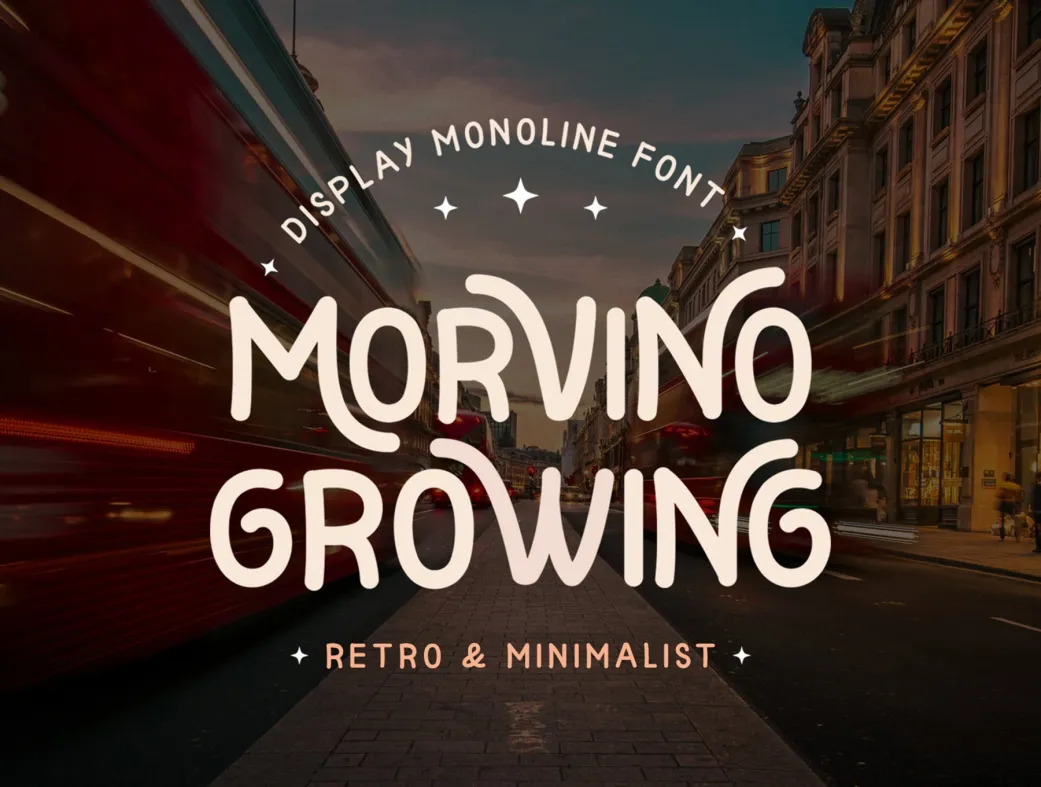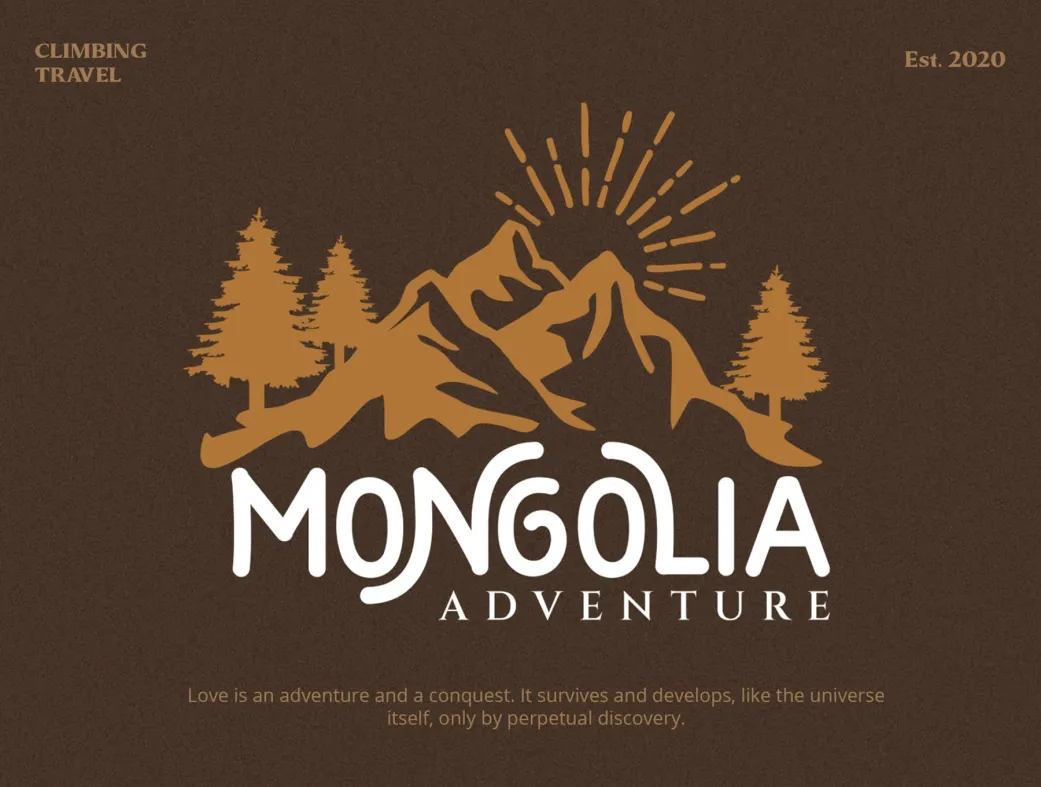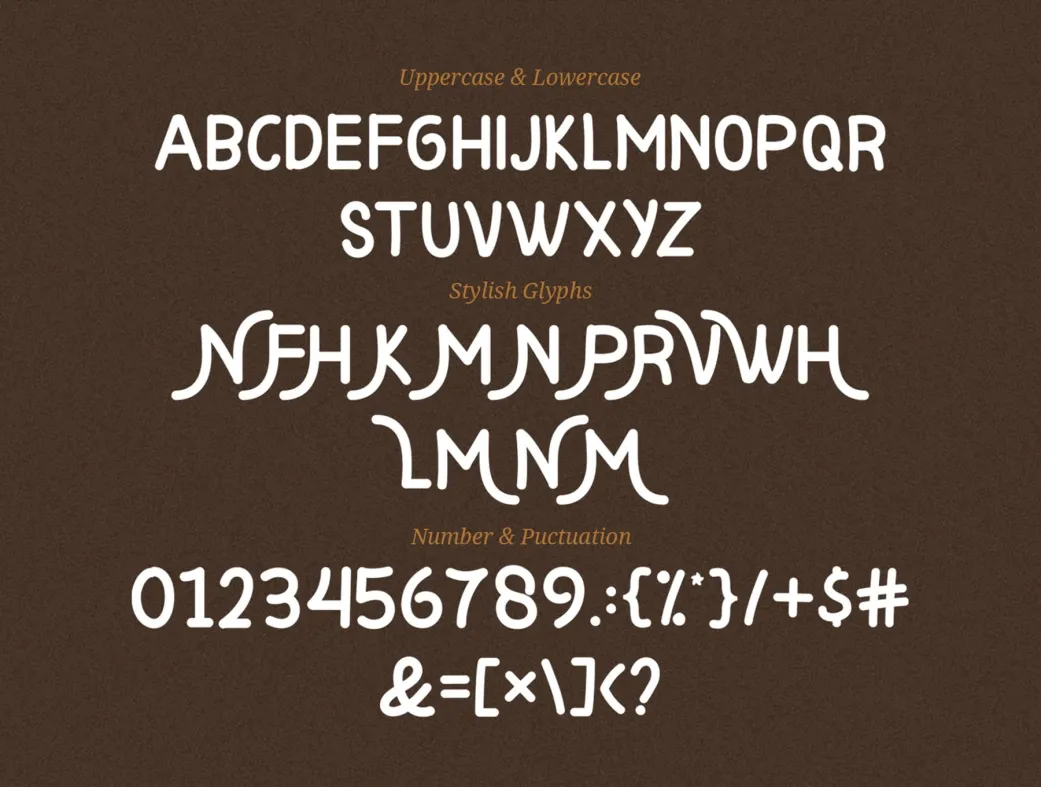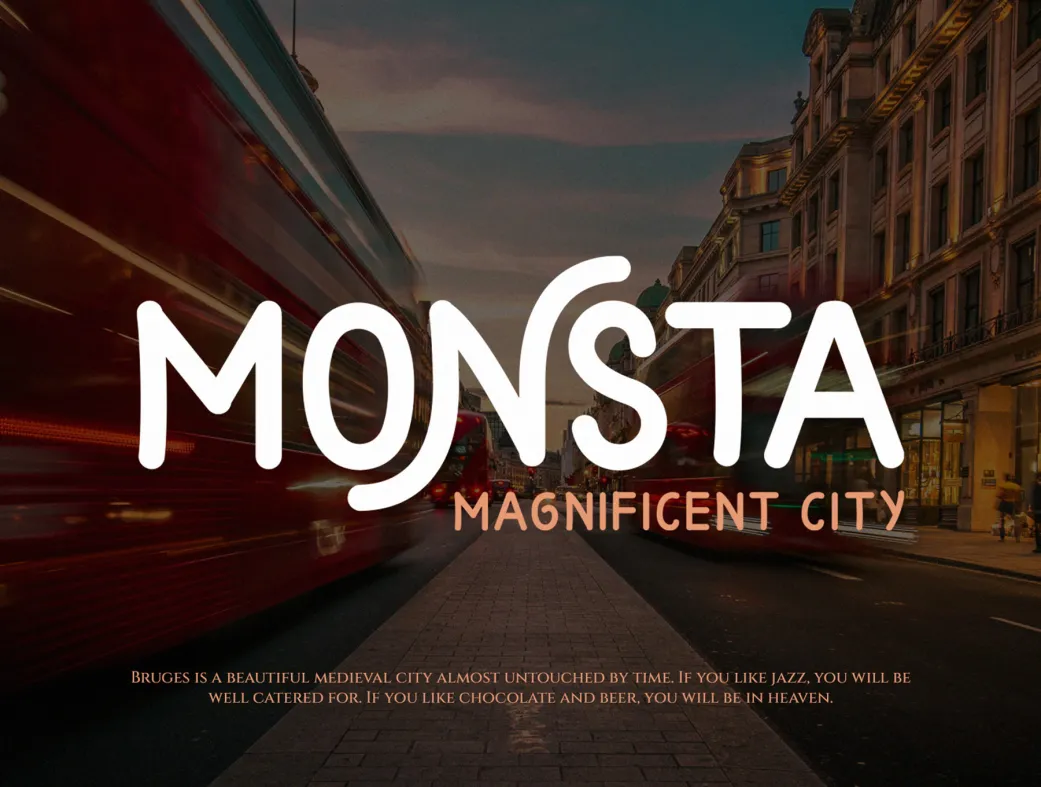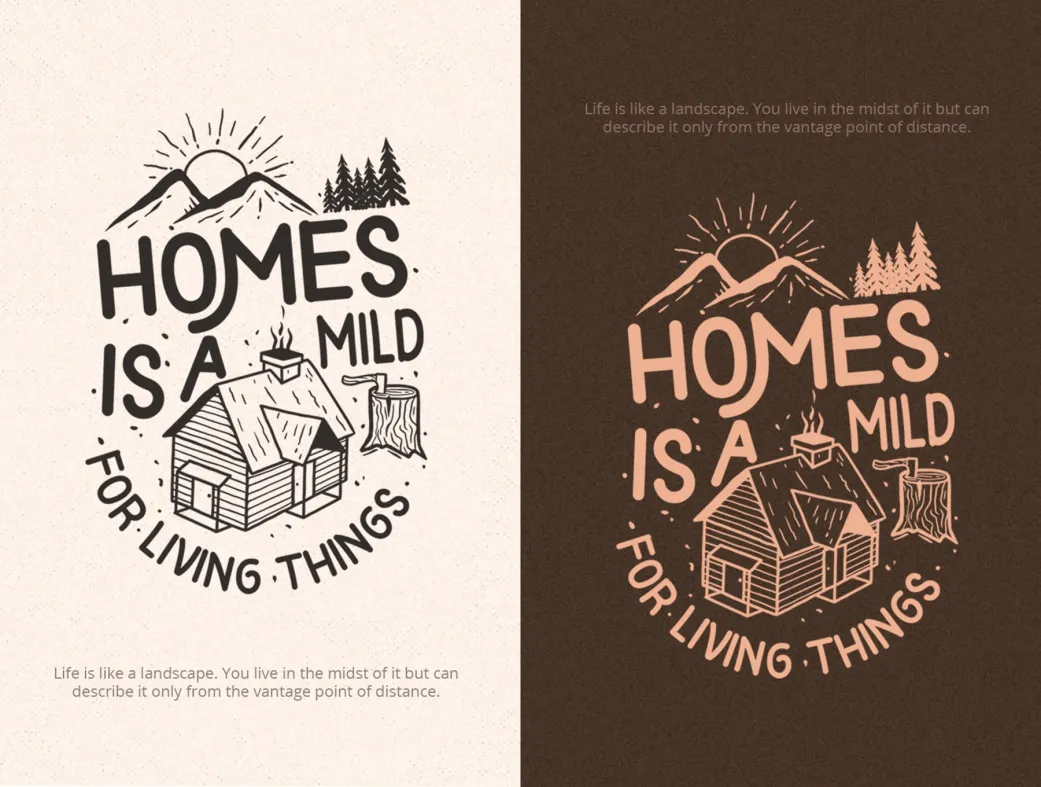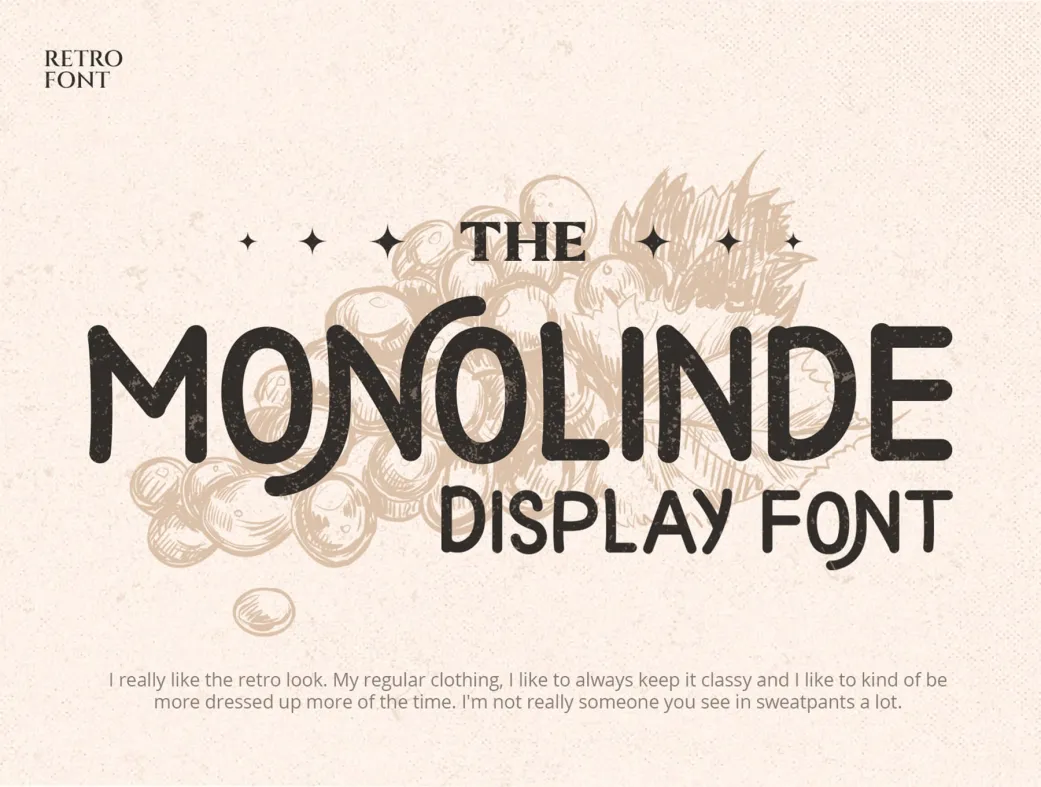
معرفی فونت موروینو گروینگ
موروینو گروینگ یک فونت نمایش مونولاین با ترکیبی بینظیر از سبک مدرن و رترو است. این فونت برای طراحان ایرانی که به دنبال فونتهای خاص و جذاب هستند، انتخابی عالی محسوب میشود.
ویژگیها و مزایای فونت موروینو گروینگ
این فونت با خطوط ظریف و یکنواخت خود، حس حرفهای و در عین حال نوستالژیک ایجاد میکند. مناسب برای پروژههایی که نیاز به تعادل بین مدرنیته و حس کلاسیک دارند.
کاربردهای موروینو گروینگ
طراحی بستهبندی محصولات و صنایع دستی
برندینگ و لوگو برای کسبوکارهای خلاقانه
طراحی نقلقولها، پوسترها و محتوای اینستاگرامی
برچسبها، واترمارک و طراحیهای عکاسی
محصولات نوزاد و نیازهای مرتبط
موروینو گروینگ با کیفیت بالا و توجه به جزئیات، به پروژههای طراحی شما ارزش افزوده میدهد و تجربهای لذتبخش از کار با فونتهای حرفهای را فراهم میکند.